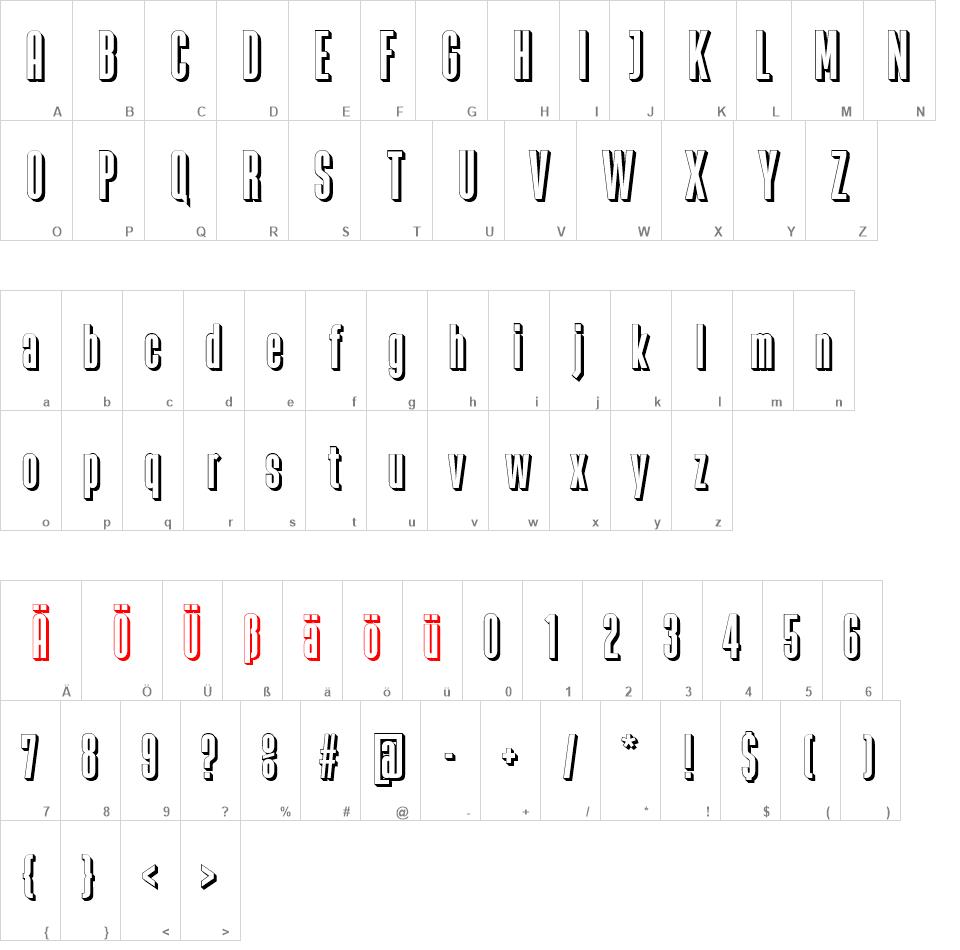
Zacatecas
Zacatecas ist eine Schattenschrift ohne Serifen und komprimierte, sehr einfache geometrische Formen, eine schmucklose, nüchterne Displayschrift, die großen Platz spart.